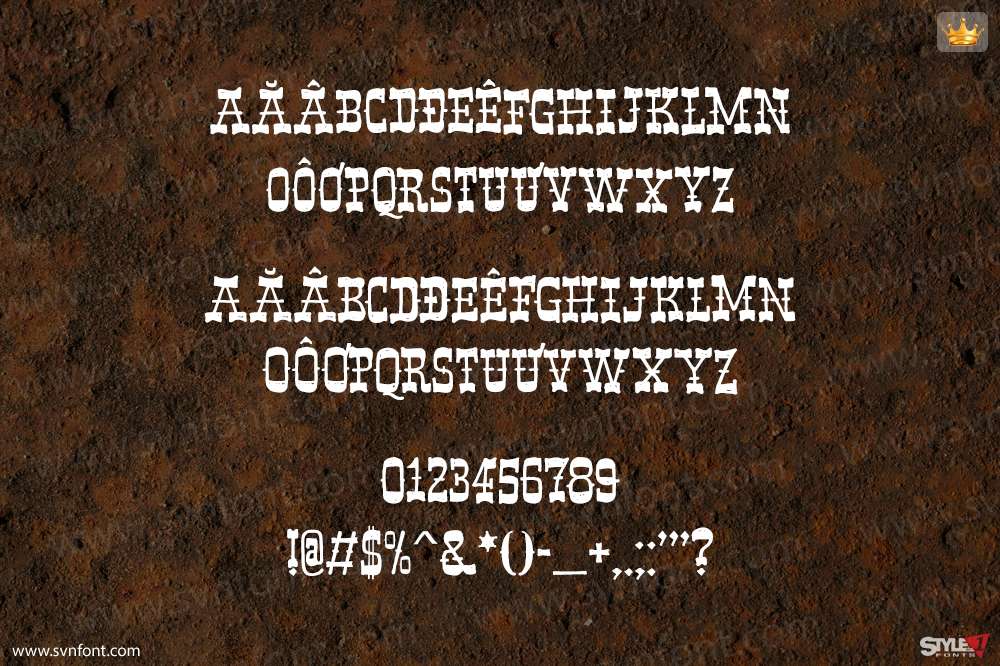
Tôi không biết chính xác tại sao, nhưng tôi cảm thấy cần phải tạo ra một phông chữ miền Tây. Band Wagon là một phông chữ cao bồi thủ công. Nó đi kèm với các nét serif cong, các chi tiết hình cựa và tinh thần của những tên tội phạm xưa cũ.